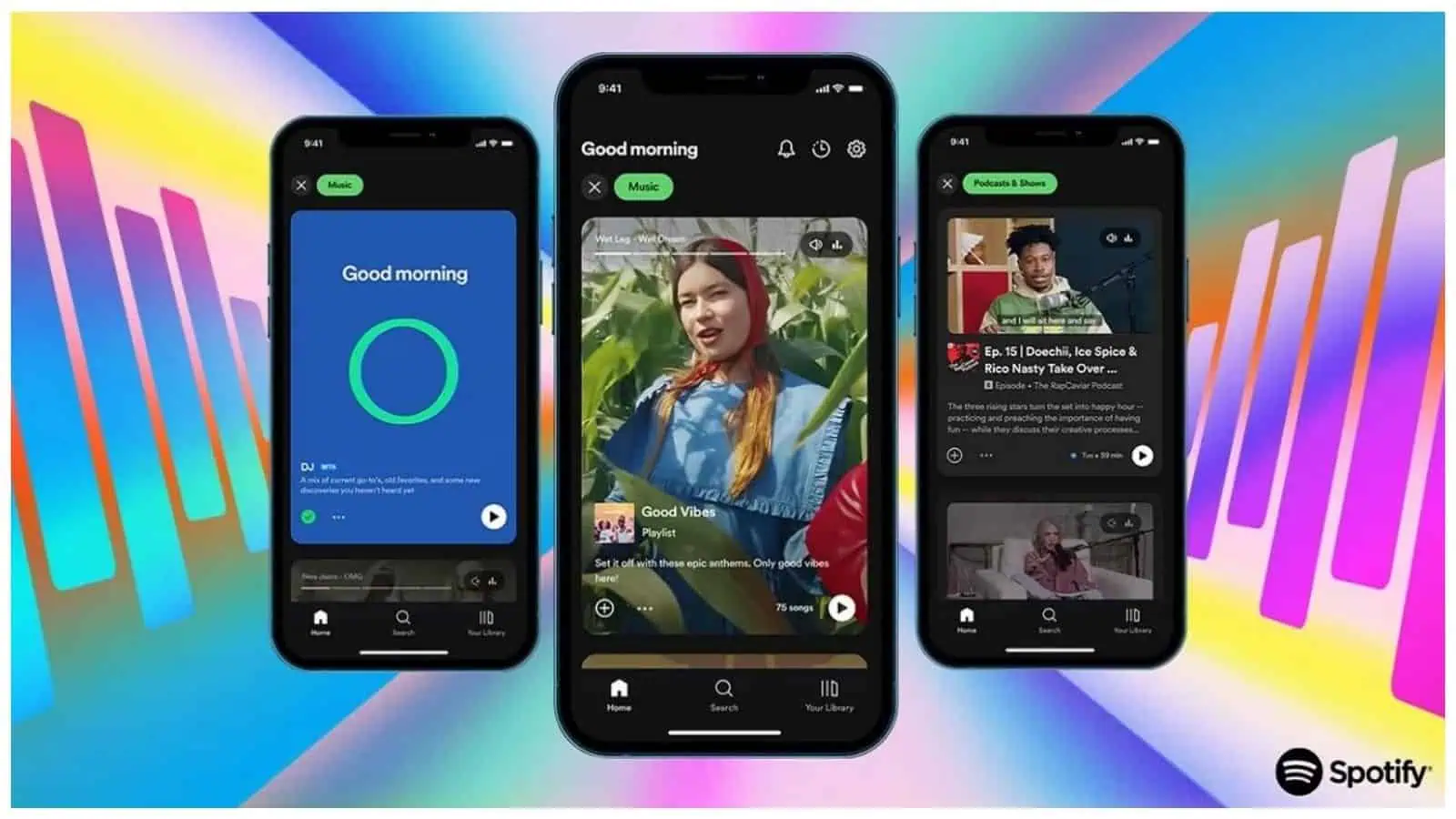
Spotify cambia il suo design: il nuovo font stupisce tutti
Spotify, leader indiscusso nell’ambito dello streaming musicale, di recente ha inaugurato un nuovo capitolo della sua storia con il lancio del font “SpotifyMix”. Questo audace progetto di rinnovamento grafico rappresenta un importante passo nell’evoluzione dell’identità visiva della piattaforma. In quanto contribuisce ad offrire una prospettiva completamente rinnovata sul modo in cui l’azienda si relaziona con il suo vasto pubblico.
Spotify Mix, molto più di un semplice font
Tale aggiornamento potrebbe essere considerato come un tributo alla natura dinamica e in costante evoluzione della cultura audio. Il nuovo font riesce a coniugare abilmente elementi provenienti da una varietà di fonti e stili diversi. Rappresenta infatti un vero e proprio remix di concetti e forme, riflettendo l’essenza stessa della creatività e dell’innovazione che caratterizzano il mondo della musica digitale. Anche la scelta del nome non è casuale, “Spotify Mix” evoca immediatamente l’idea di una miscela unica e originale. Un mashup capace di trasformarsi e adattarsi in modo fluido ai diversi contesti e alle diverse esigenze comunicative.
Descritto come un font “sans serif“, privo di orpelli e appendici superflue, “SpotifyMix” è una combinazione sorprendente di elementi classici e contemporanei. Le sottili allusioni alle onde sonore integrate nel design evocano una sensazione di ritmo e movimento. Mentre la fusione di curve fluide e spigoli vivi gli regala una personalità vibrante e distintiva. È proprio questa versatilità intrinseca che rende il Mix la scelta ideale per l’implementazione su tutte le piattaforme e le applicazioni della compagnia. Dalle playlist alle copertine degli album, fino alle campagne di marketing e alle comunicazioni ufficiali.
Come è nato il nuovo progetto
Per portare a termine questa rivoluzionaria innovazione l’ azienda ha collaborato con lo studio di design Dinamo Typefaces, con sede a Berlino. L’obiettivo era chiaro sin dall’inizio. Ovvero creare un font che rispecchiasse l’identità e lo spirito di Spotify. Ma che offrisse anche agli artisti e ai creatori di contenuti la possibilità di esprimere la propria creatività. Ciò in modo più autentico e coinvolgente possibile. Il risultato, come già detto, va molto oltre il semplice aspetto estetico. Diventando un catalizzatore per la comunicazione visiva e un simbolo tangibile dell’impegno della società.